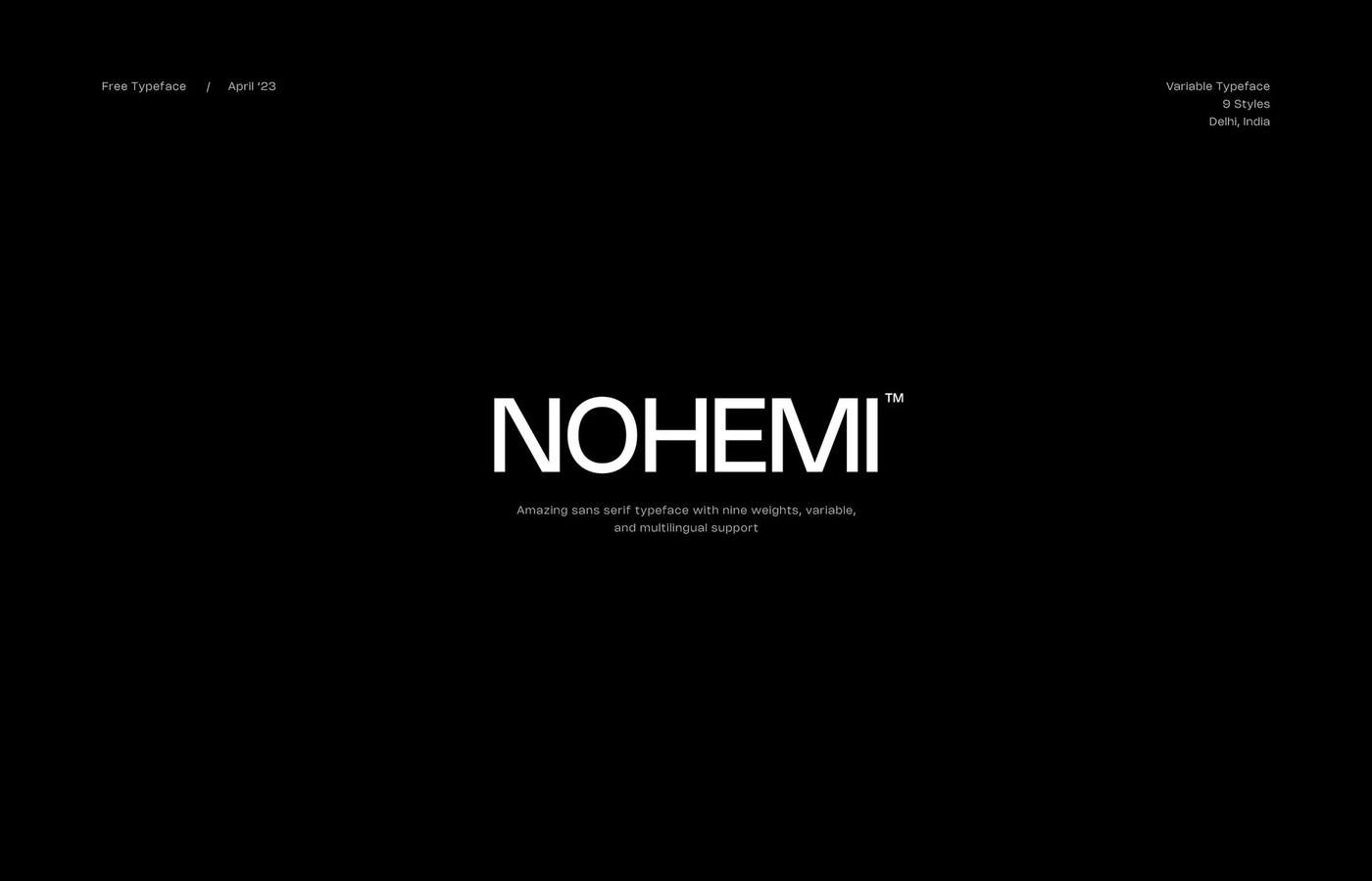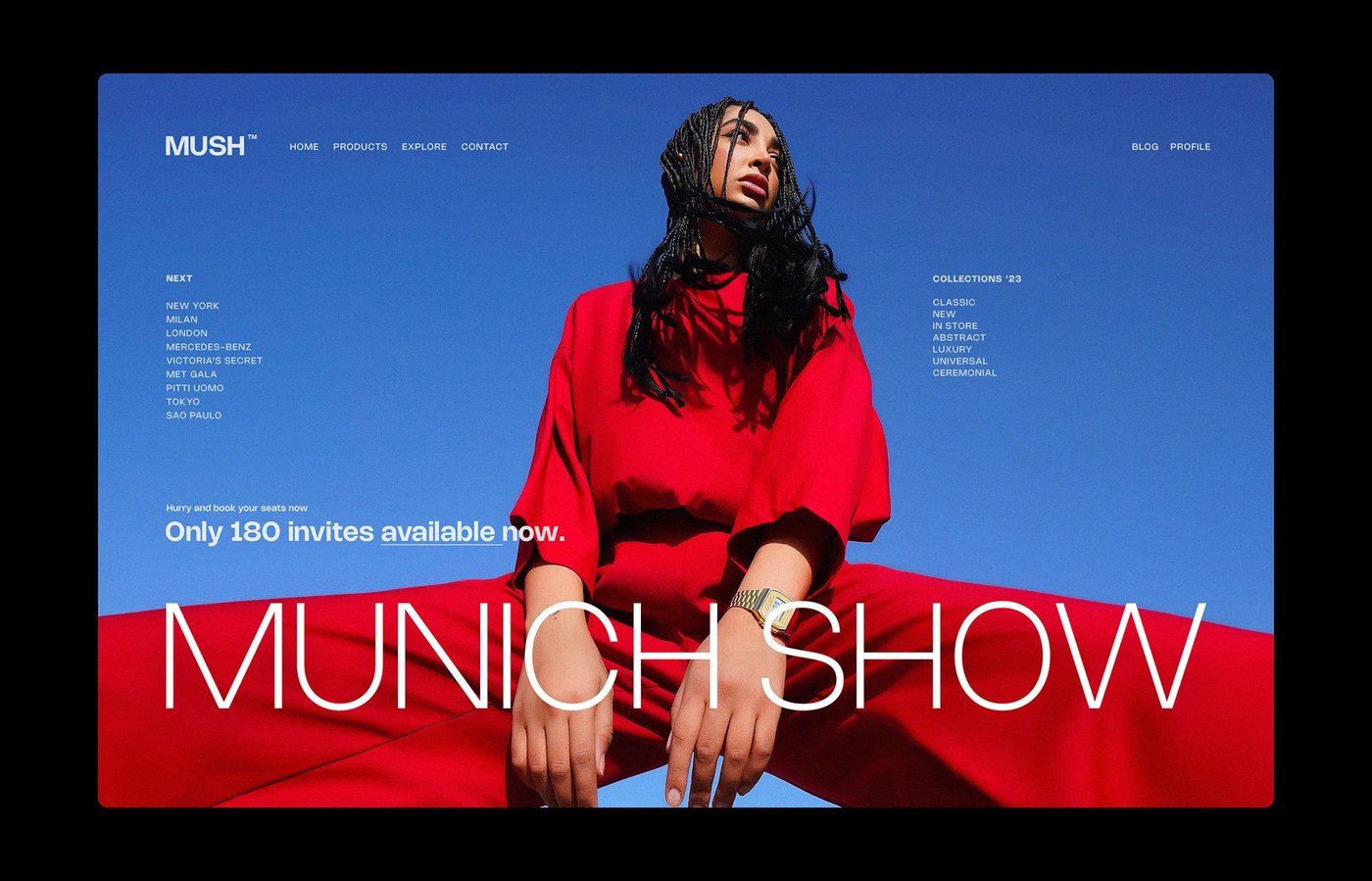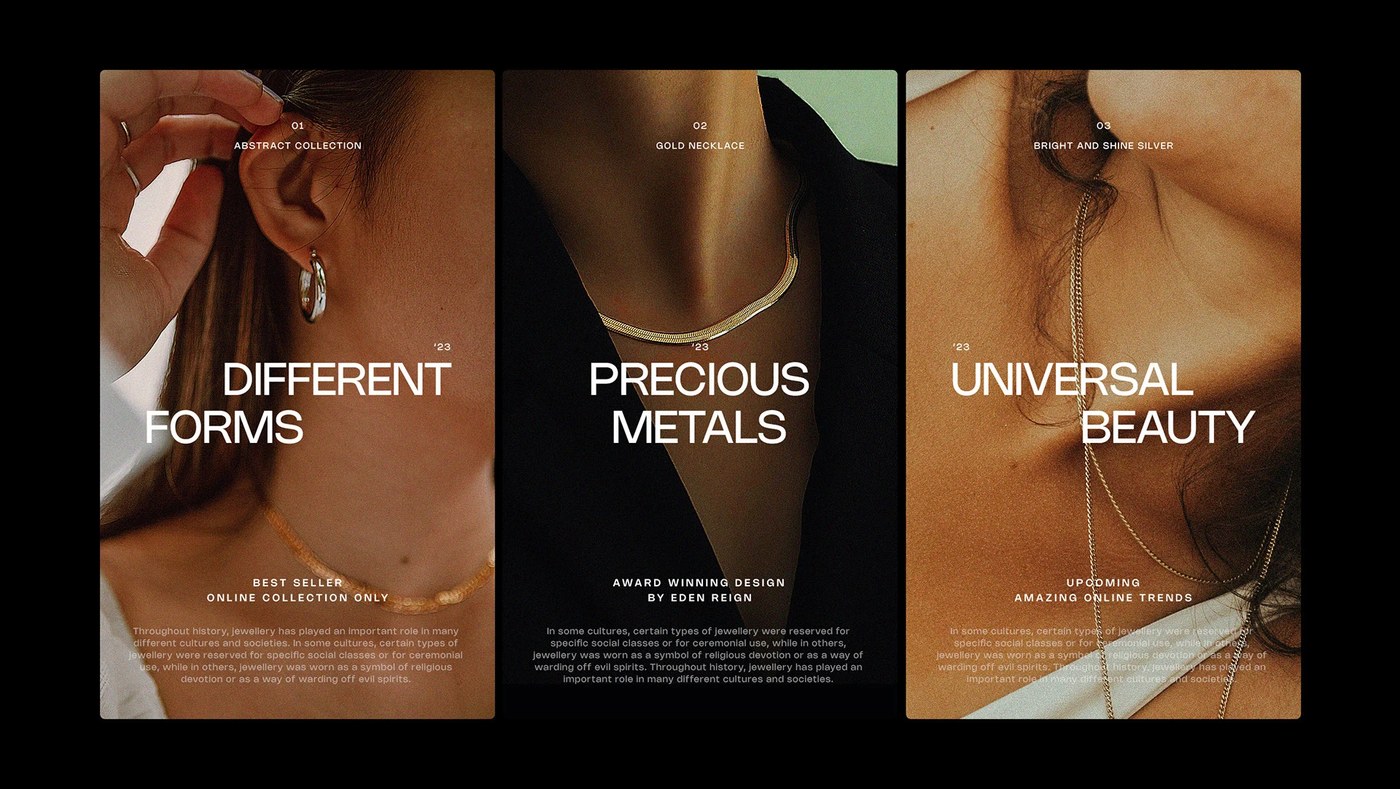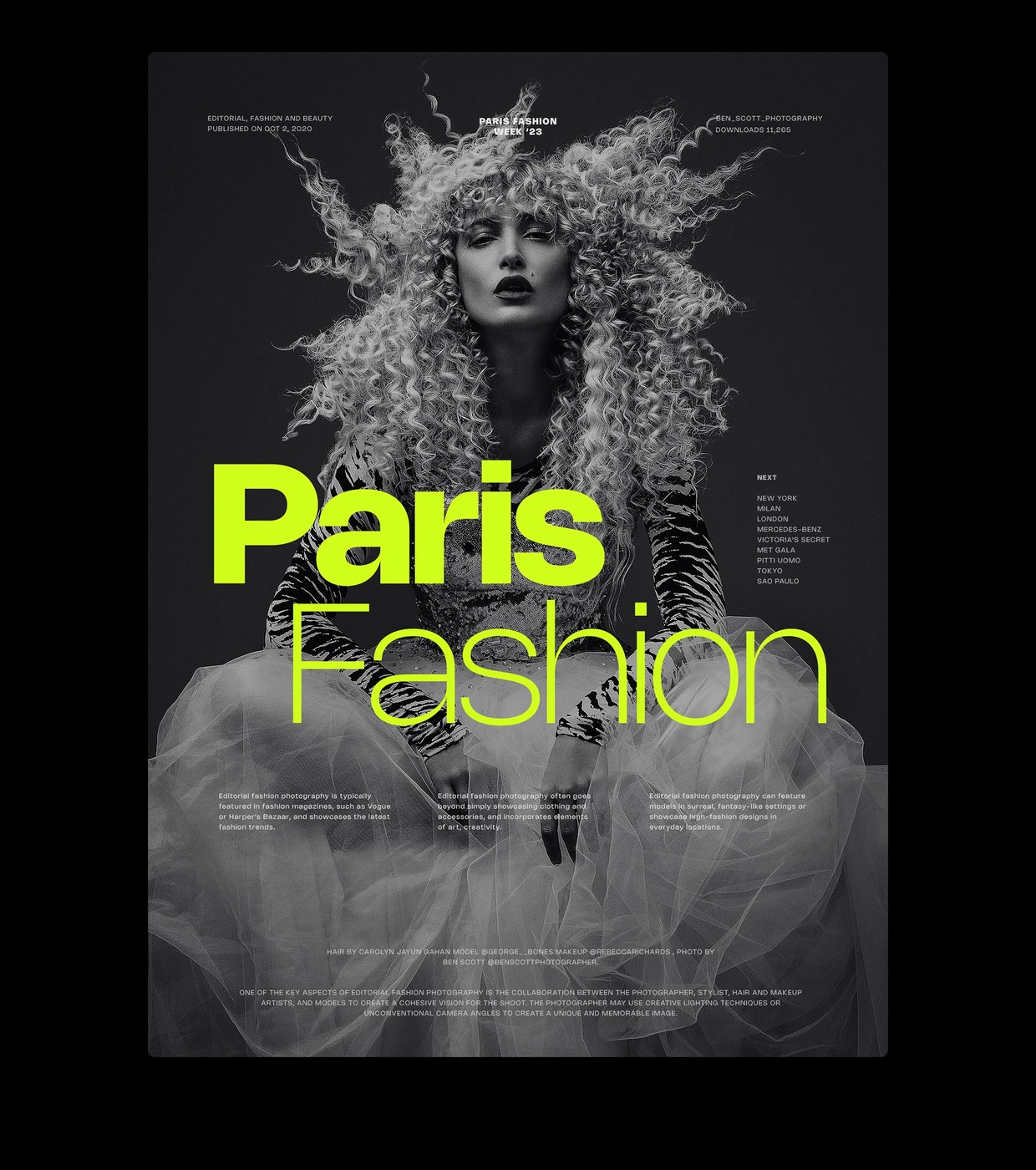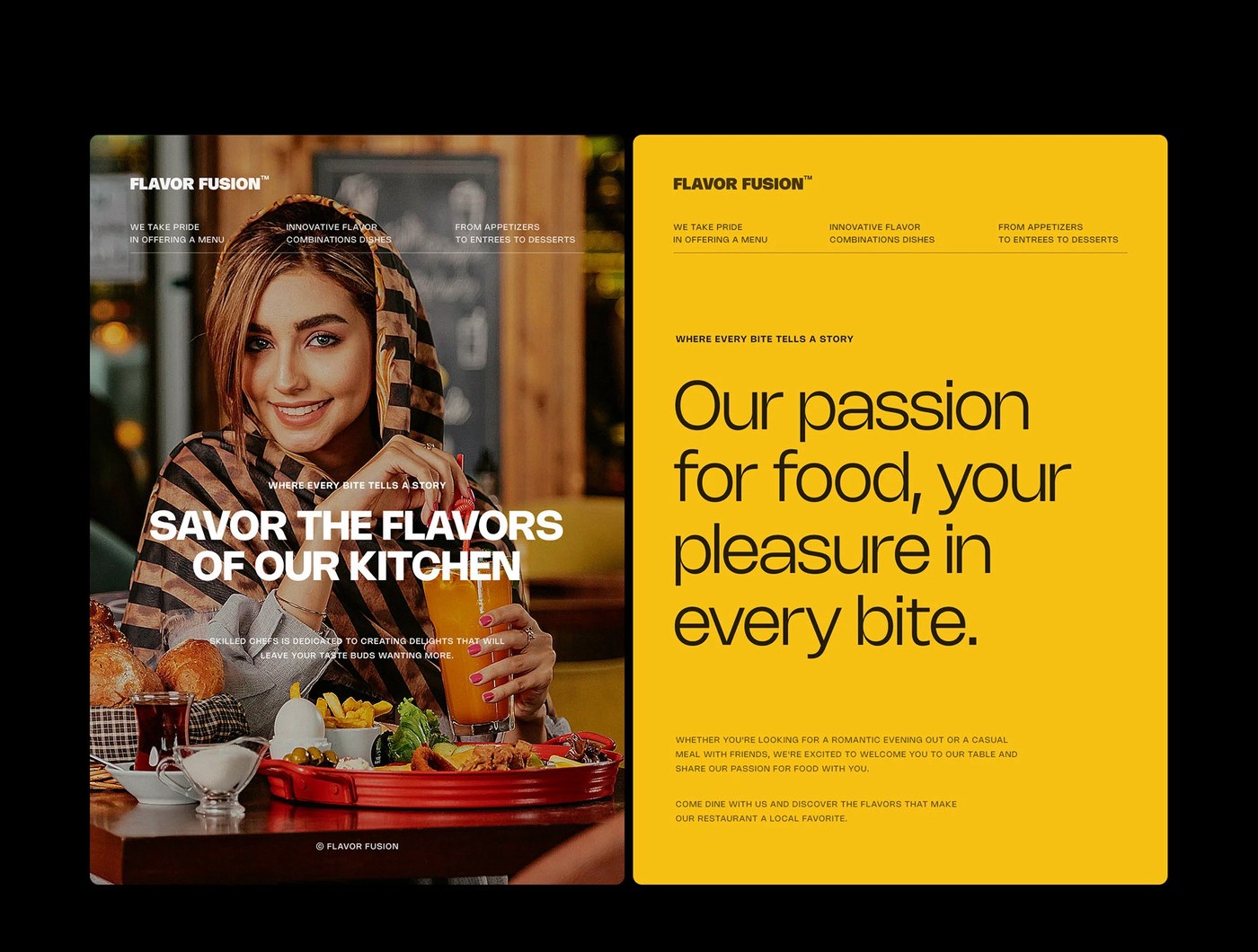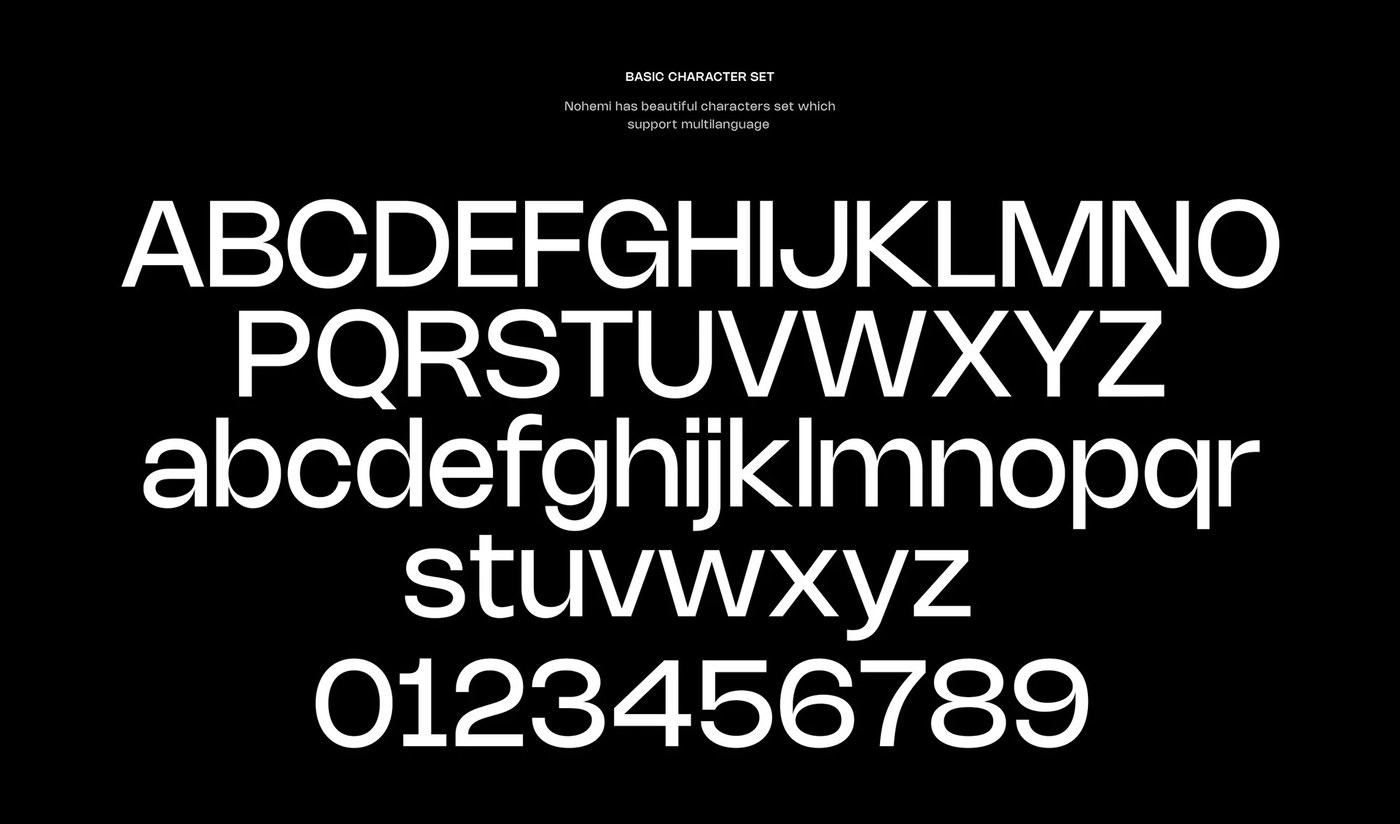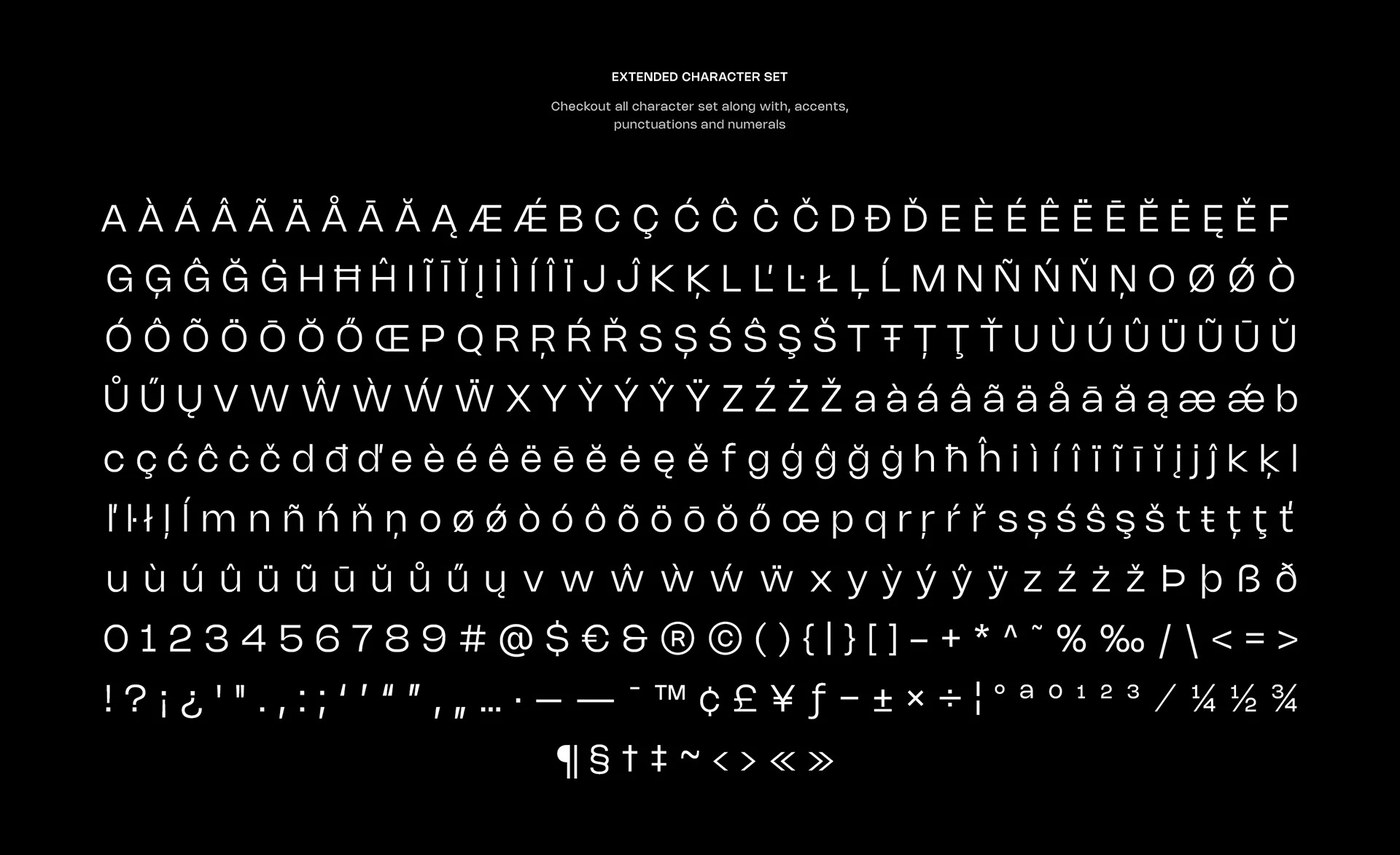
Một “vũ khí” thiết kế cực xịn vừa xuất hiện dành cho hội mê chữ nghĩa! Đó chính là Nohemi – bộ display typeface dạng variable font siêu chất đến từ designer Rajesh Rajput. Sáng tạo này mang đậm phong cách Swiss design sạch sẽ kết hợp cùng tư duy hình khối (geometric) tối giản, hứa hẹn sẽ làm bừng sáng mọi layout hiện đại.
Các ký tự của Nohemi được xây dựng trên hệ thống lưới mô-đun (modular grids) vô cùng chuẩn chỉnh. Sự kết hợp giữa các khoảng trống âm (negative space) lớn tạo nên một nhịp điệu thị giác sắc sảo, giúp font chữ dễ dàng chiếm trọn spotlight mà không cần đến các chi tiết trang trí rườm rà. Các đường cong hình học phẳng cùng quy tắc khoảng cách (spacing) được căn chỉnh tỉ mỉ giúp việc tổ chức thông tin phức tạp trở nên dễ dàng hơn bao giờ hết. Dù ở kích thước nào, cấu trúc của Nohemi vẫn cực kỳ vững chãi, tạo điểm tựa hoàn hảo cho các phần tiêu đề (headlines).
Điểm cộng lớn nhất của bộ font này chính là hệ thống trục variable với 9 độ dày (weights) khác nhau đầy linh hoạt. Bộ ký tự có khả năng chuyển đổi mượt mà từ những nét light thanh mảnh, bay bổng cho đến các nét heavy đậm chất kiến trúc mạnh mẽ. Nhờ vậy, Nohemi có thể cân đẹp từ những tiêu đề cỡ đại cho đến các phần chú thích nhỏ. Không chỉ tỏa sáng trên các ấn phẩm poster vật lý, font chữ này còn tối ưu rất tốt trên màn hình kỹ thuật số, đảm bảo độ hiển thị sắc nét và dễ đọc ngay cả trên thiết bị di động.
Có thể thấy, Rajesh Rajput đã tạo ra một công cụ thiết kế vô cùng tinh tế, mang hơi thở hiện đại của năm 2026 nhưng vẫn kế thừa trọn vẹn tinh thần Swiss modernism cổ điển. Các designer hoàn toàn có thể kết hợp những ký tự cô đọng (condensed glyphs) của Nohemi với các font thuộc họ grotesque rộng hơn để tạo nên một hệ thống phân cấp thị giác (hierarchy) chuẩn chỉnh cho các dự án editorial hay thiết kế nhận diện thương hiệu.
A seriously sleek new design weapon just dropped for all the typography lovers out there! Meet Nohemi—a super cool variable display typeface created by designer Rajesh Rajput. Heavily inspired by clean Swiss design and minimalist geometric concepts, this creation is bound to make any modern layout pop.
Nohemi’s characters are built on incredibly precise modular grids. The blend of generous negative space creates a sharp visual rhythm, allowing the font to easily steal the spotlight without needing any flashy or redundant details. Flat geometric curves combined with meticulously tuned spacing rules make organizing complex information easier than ever. No matter the size, Nohemi’s structure remains rock-solid, making it the perfect anchor for bold headlines.
The biggest highlight of this font family is definitely its flexible variable axis featuring 9 different weights. The character set smoothly transitions from delicate, airy light weights to powerful, architecturally bold heavy weights. Because of this adaptability, Nohemi effortlessly handles everything from massive headlines to tiny captions. It doesn’t just look amazing on physical posters, either—it’s also highly optimized for digital screens, ensuring crisp and readable rendering even on mobile devices.
Rajesh Rajput has truly delivered an incredibly sophisticated design tool that feels fresh and modern for 2026 while fully honoring classic Swiss modernism. Designers can easily pair Nohemi’s condensed glyphs with wider grotesque font families to build a flawless visual hierarchy for editorial layouts or brand identity projects.